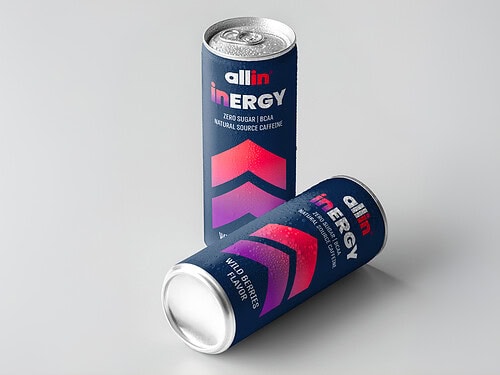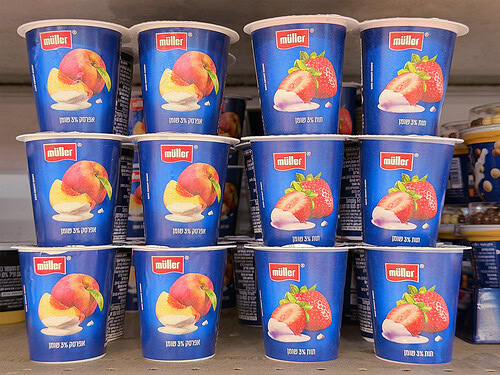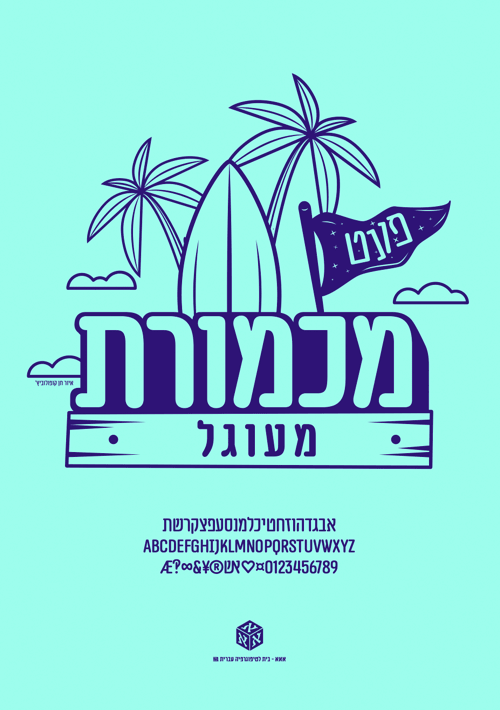
אחיו השובב של פונט מכמורת שנולד מתוך שלט הכניסה של מושב מכמורת
The entrance sign to the village of Mikhmoret became the starting point for the design of this contemporary Hebrew and Latin typeface
פונט מכמורת מעוגל הוא פונט דו־לשוני צר ויציב, בעל צורניות מעוגלת וחיננית. יש לו גישה ניואנסית מפתיעה - דבר שמקנה לו אופי ייחודי ומובחן. יחד עם האותיות הלטיניות (Capitals), זהו פונט שימושי מאד לכותרות עוצמתיות מצד אחד וטקסטים קצרצרים וקלילים מצד שני.
Conceived from the old entrance sign to the village of Mikhmoret, the Mikhmoret typeface continued to grow while drawing inspiration from classical Hebrew fonts such as Aharoni and the wooden type blocks of the 1940’s.
על אודות פונט מכמורת מעוגל
פונט מכמורת מעוגל נולד מתוך שלט הכניסה הותיק של מושב מכמורת, והמשיך להתפתח דרך הישענות על מקורות השראה של פונטים עבריים קלאסיים כמו גופן אהרוני ואותיות עץ משנות ה־40. זהו פונט דו־לשוני צר ויציב, בעל צורניות מעוגלת וחיננית. יש לו גישה ניואנסית מפתיעה - דבר שמקנה לו אופי ייחודי ומובחן. יחד עם האותיות הלטיניות (Capitals), זהו פונט שימושי מאד לכותרות עוצמתיות מצד אחד וטקסטים קצרצרים וקלילים מצד שני.
המלצת המערכת
מתאים מאוד לכרזות, לוגואים ועל אריזות צעירות.
OpenType Features
- ליגטורות אשקלון ← אשקלון
- ליגטורות סודיות בע״מ ← בע״מ
- סימנים בגבהים שונים מתי? ← מתי?
- אפס מלוכסן 0 ← 0